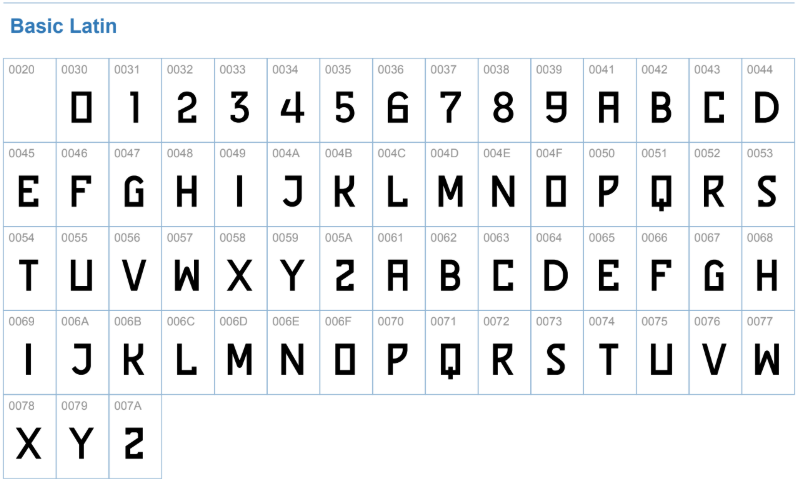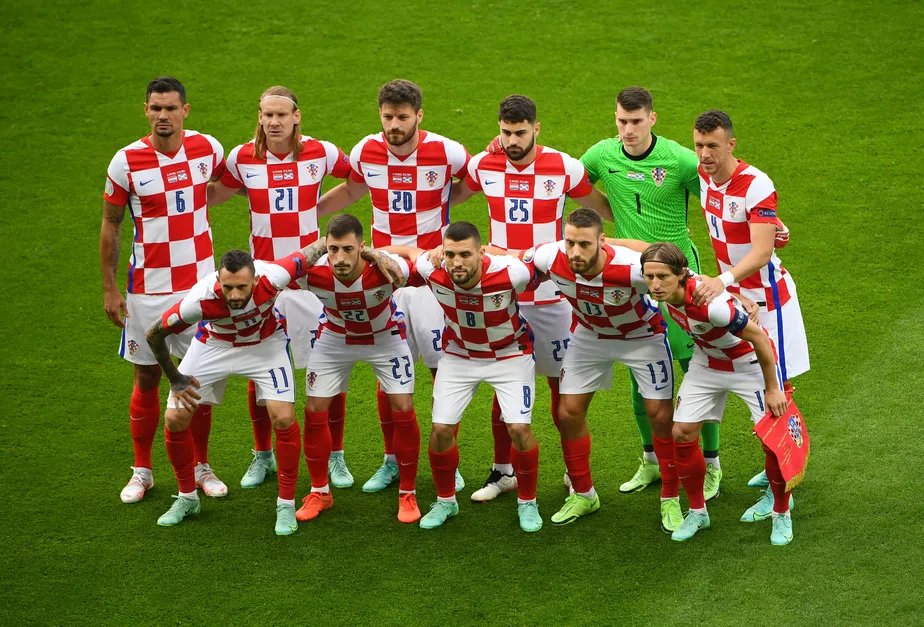
O ano de 2026 marca mais um capítulo dourado para a seleção croata, agora de olho na Copa do Mundo que será disputada na América do Norte.
Com um elenco que mescla a experiência de uma geração semifinalista e novos talentos, a identidade visual do time ganha atenção redobrada. Cada detalhe conta, e a tipografia oficial é a assinatura que fecha o uniforme com personalidade.
Designers, colecionadores e torcedores fanáticos por camisas já sabem: a fonte dos números e nomes transforma um layout comum em um ícone imediato. É ela que grita “Croácia” antes mesmo de a câmera fechar no escudo quadriculado. Por isso, preparamos um raio-x completo da fonte que veste os Vatreni em 2026 e, claro, o caminho para você baixar a versão inspirada no estilo oficial.
Estilo visual da tipografia
A fonte Croácia 2026 aposta em traços retos e terminações levemente angulares, um aceno ao design geométrico do brasão nacional. Os números trazem recortes internos que melhoram a leitura em velocidade, enquanto as hastes têm espessura consistente para não “estourar” na transmissão em 4K.
O aspecto geral entrega modernidade sem abrir mão da tradição — a inspiração principal vem das famosas camisas quadriculadas, mas filtrada por um minimalismo técnico que funciona tanto no gramado quanto na tela do celular.
A legibilidade em movimento é o ponto forte. A altura generosa das letras e o espaçamento calibrado evitam que nomes como “Gvardiol” ou “Modrić” se embaracem mesmo nos replays mais rápidos. Ao vivo, a fonte respira personalidade: é agressiva no ataque, mas limpa o suficiente para agradar designers que buscam um visual esportivo premium.
Aplicação no uniforme
No manto Home, o quadriculado vermelho e branco recebe a tipografia em branco com um fino outline azul royal, resgatando um contraste que remete à bandeira. A numeração ganha presença sem brigar com o padrão xadrez.
Para o uniforme Away, que deve explorar o azul marinho como base, os nomes e números aparecem em vermelho vibrante com acabamento fosco — fácil de identificar até de longe. Já a opção Third, ainda especulada em tom off-white com detalhes dourados, traria a fonte vazada em ouro, elevando a camisa a um status quase celebratório.